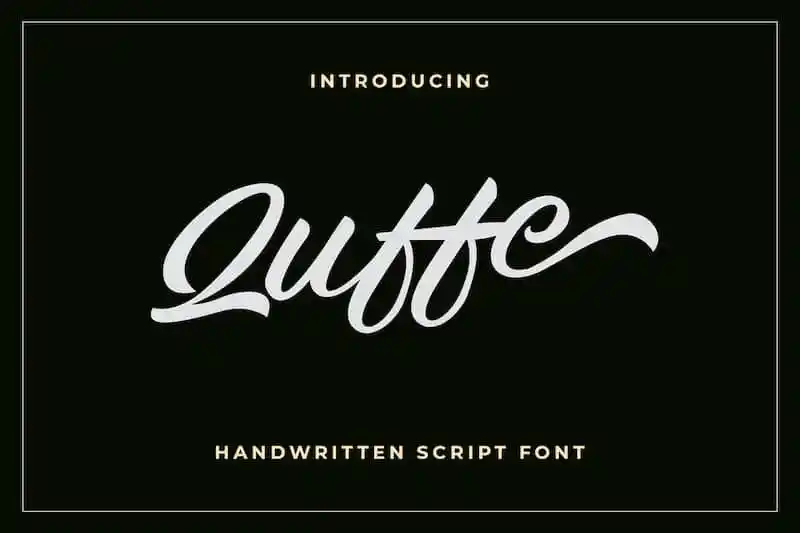
Quffe Script Font – Download Grátis
A Quffe Script Font é uma elegante escolha para aqueles que procuram adicionar um toque moderno e sofisticado às suas criações digitais. Esta nova opção de fontes script foi criada por Maulana Creative, oferecendo uma experiência visual atraente e autêntica. Suas linhas fluidas e delicadas são ideais para designers buscando dar brilho aos seus projetos, seja para criar convites de casamento sofisticados, arte de estação encantadora ou conteúdo social que chama atenção dos seguidores, até mesmo cartões de agradecimento leves e divertidos. A Quffe Script é uma opção perfeita para incorporar em suas próximas criações digitais, tornando-as ainda mais memoráveis.